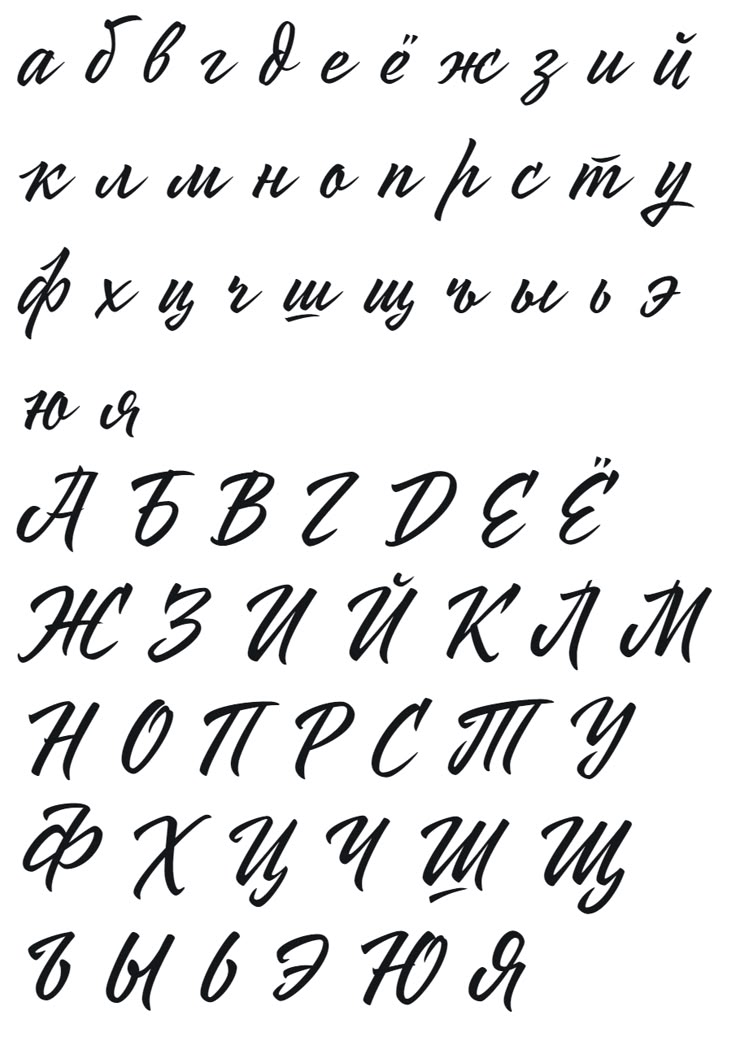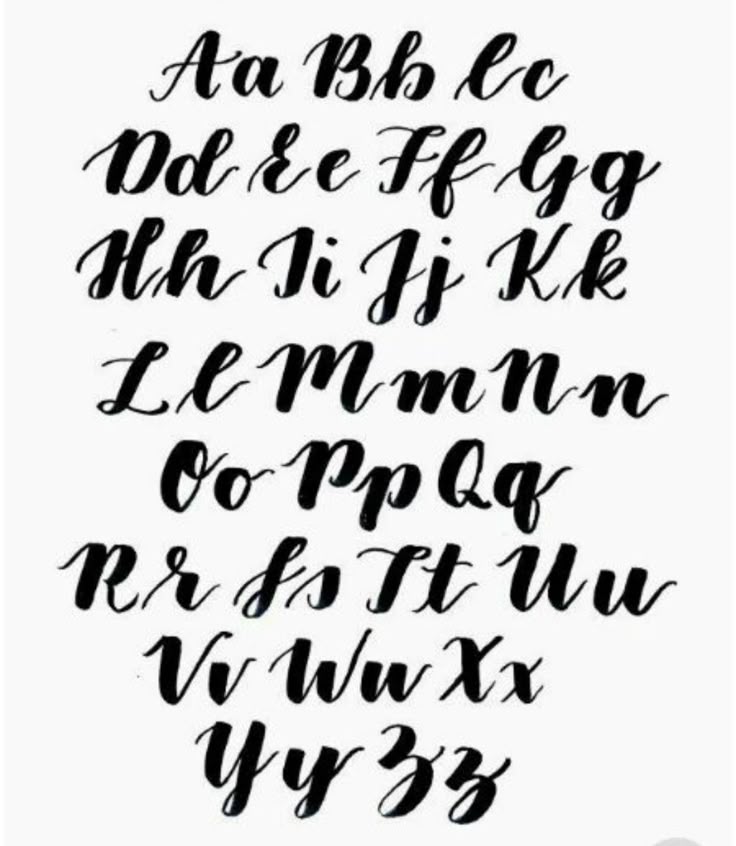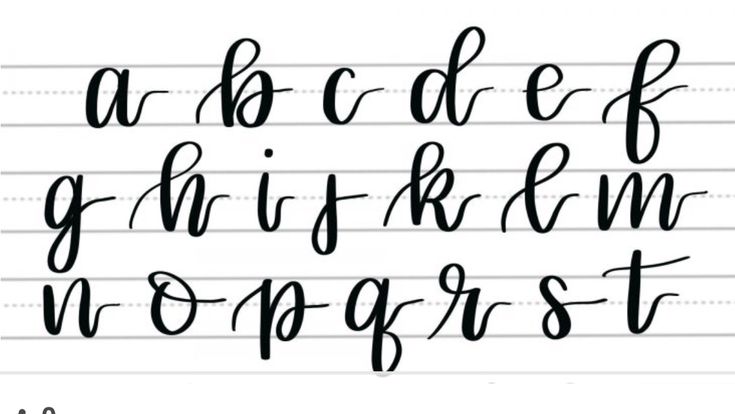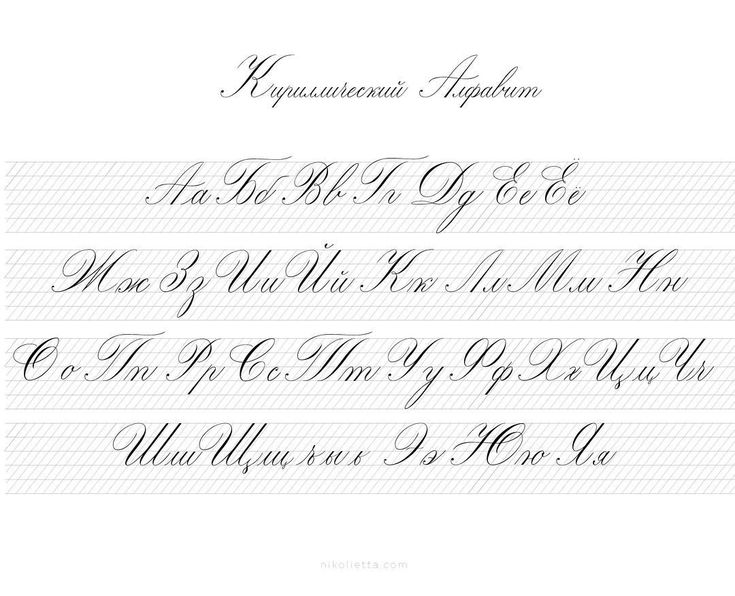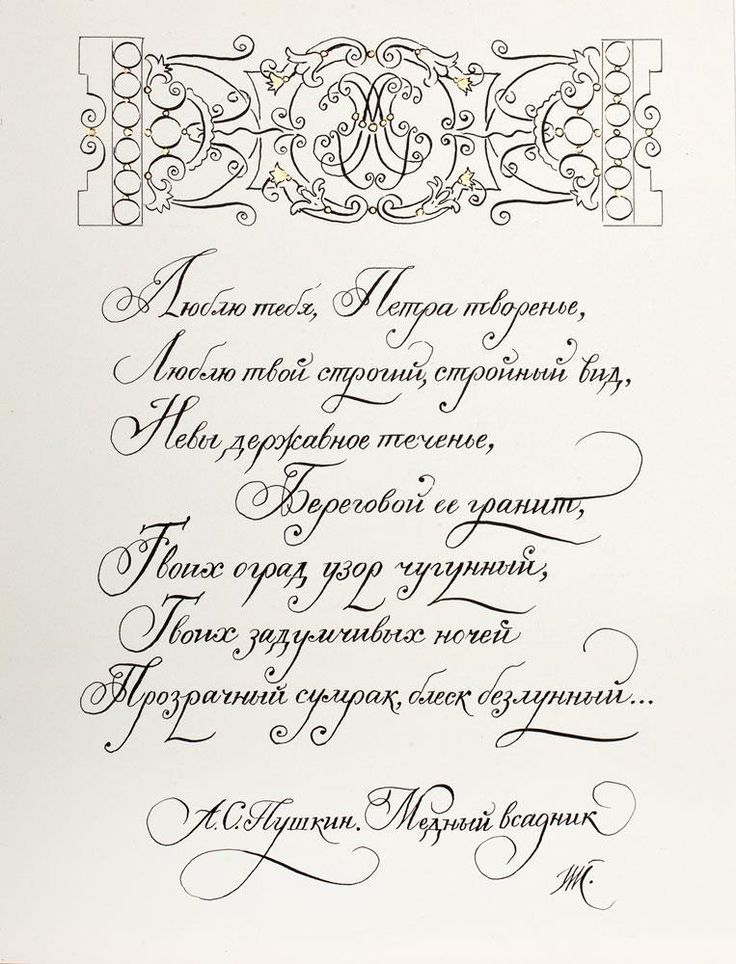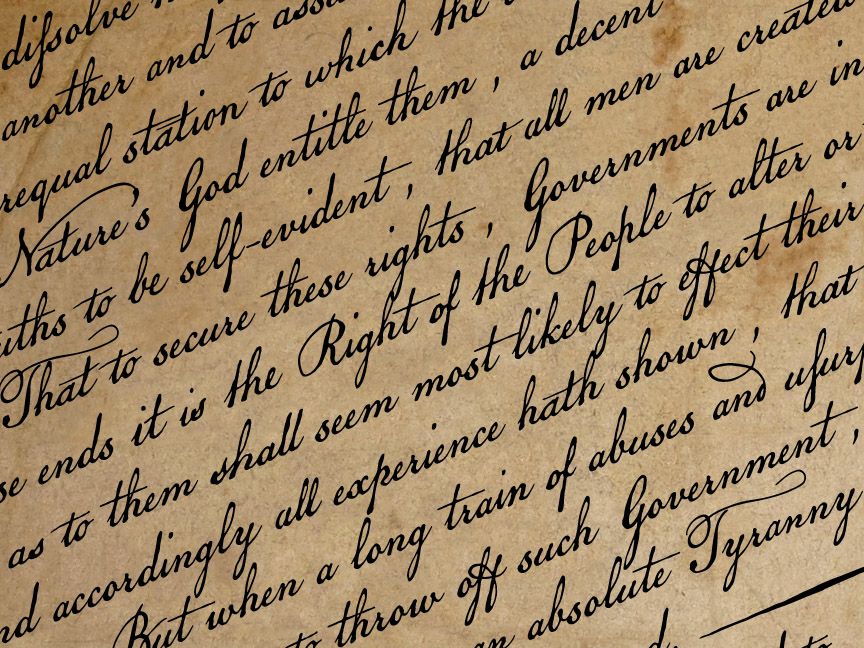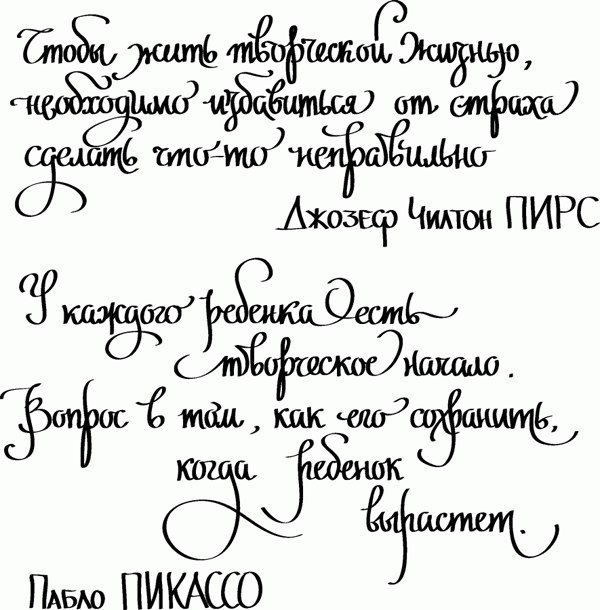
Рукописные шрифты и графология
Замысел статьи возник случайно. В руках графолога, далёкого от компьютерной техники, оказалось письмо, набранное шрифтом Коррида. «Какой противоречивый характер, — воскликнул он. — Что за человек это писал? Кто он?»
Автор объяснил, что этого человека на самом деле не существует. И тут же возникла идея — рассмотреть вопрос подробнее. Вообще-то, графология не относится к сверхпопулярным дисциплинам, но требование представить, например, написанное от руки резюме при приёме на работу встречается не столь уж редко. Малоизвестность графологии и даже недоверие к ней — результат многолетней политики, при которой популяризация подобного рода инструментария считалась излишней.
Между тем, нас не удивляет, что темперамент и характер человека проявляются в десятках жизненных мелочей: в манере завязывать галстук или затачивать карандаши, в выборе породы собаки, в цвете любимого авто, даже в том, как расходуется столбик губной помады и стаптываются подошвы ботинок.
Тем более странно, если б наши личные качества не находили полного отражения в таком тонком и тесно связанном с деятельностью мозга процессе, как письмо от руки. Вот что говорится об этом в специальной литературе: «Данное положение является логическим следствием представлений о системном строении психики и мозга… Все психические процессы (действия) складываются как сложное целое, состоящее из взаимосвязанных между собой частей (или звеньев), и обеспечиваются набором действующих мозговых структур, объединённых в функциональные органы… Одно и то же звено может входить в различные психические процессы, соединяя их в этой общей точке пересечения. Соответственно, одна и та же структура мозга участвует в образовании нескольких психических функций… Письмо как специальное психическое действие является сложным, многогранным процессом, в котором принимает участие большое количество мозговых областей, каждая из которых вносит свой специфический вклад в этот процесс» [1].
С учётом сказанного связь между почерком и такими качествами, как вспыльчивость, болезненность или болтливость, уже не кажется фантастической.
Каллиграфия против графологии
Автору неизвестен ни один пример, когда рукописный шрифт строился бы на графологической основе. Практически все разрабатываются по наитию, с немалой долей случайности, следствием чего может стать неожиданный результат. Так, в каталоге шрифтов компании ParaType тридцать рукописных гарнитур, разных по качеству, характеру и происхождению. Любопытно рассмотреть их с точки зрения графолога.
Исключим сразу группу шрифтов, основанных на канонических почерках разных стран и времён. Таковы ITC Цапф Чансери, Инглиш 157, Прописи, Петровская скоропись,
Шрифт ITC Цапф Чансери (дизайнер Герман Цапф, кириллическая часть доработана Владимиром Ефимовым при участии Геннадия Барышникова) основан на курсивных почерках эпохи итальянского Возрождения, в особенности писцов Папской канцелярии в Риме. Инглиш 157 (версия фирмы Bitstream шрифта Английский рукописный фирмы Berthold, кириллическая версия Владимира Ефимова) — шрифт в стиле английской каллиграфии XIX века. Название Прописи (дизайнер Манвел Шмавонян) говорит само за себя. Шрифт Петровская скоропись (дизайнер Геннадий Фридман) создан на основе образцов русской рукописной скорописи начала XVIII в. Каллиграфические почерки — предмет искусства, и графология их не рассматривает. Не несут личной информации прописи, стандартизованный чертёжный почерк и т. п.
«Личностные» шрифты
На другом полюсе находятся четыре варианта шрифта Пушкин (дизайнер Геннадий Фридман) и любые заказные шрифты, призванные точно имитировать руку конкретного человека.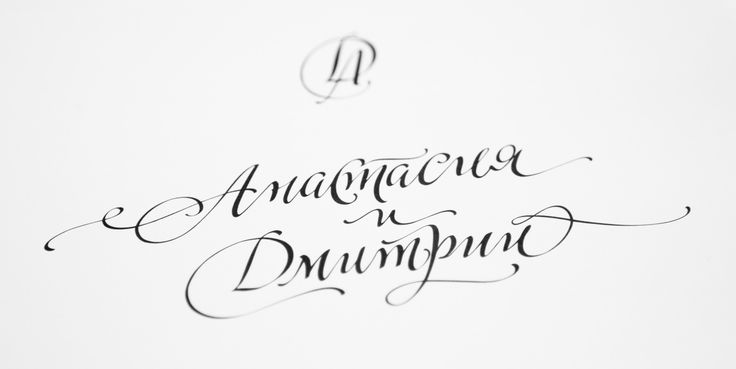
Наибольший интерес вызывают шрифты, в аннотациях к которым говорится, что «в основе лежит неформальный рукописный почерк». Их графологический анализ не столь бессмыслен, как могло бы показаться. Он даёт хотя и гипотетический, но вполне связный, логичный портрет, например, такой: «Эдвенчер — почерк энергичного, напористого, контактного человека, в котором любовь к комфорту борется с честолюбием; просматривается желание “соответствовать”, быть “на уровне”, принадлежать определённому кругу. Такой человек может предлагать необдуманные решения, настаивать на них, а в случае неудачи обвинять окружающий мир».
Разумеется, это не портрет дизайнера шрифта или человека, почерк которого послужил для шрифта прототипом, тем более что прототипов может быть несколько. Здесь могут, конечно, прослеживаться отдельные черты реальных характеров, но в сочетаниях, по которым «трудно было бы правду узнать».
Ведь истории многих шрифтов полны поворотов: шрифт может создаваться одним художником по эскизам другого, затем перерабатываться третьим, а четвёртый доделывает кириллическую часть. Получившаяся «шрифтовая личность» начинает жить собственной жизнью. Пусть читатель не может ничем объяснить своего впечатления — подсознательное влияние шрифт, безусловно, оказывает. Нетрудно предположить, например, что псевдорукописный текст, похожий на почерк доброго, умного, весёлого и лёгкого в общении собеседника, скорее всего, расположит к себе читателя, а «почерк» угрюмого неприятного субъекта будет подсознательно блокировать желание общаться. Кто знает, может быть, в этом таится ещё один, до сих пор не разработанный метод рекламного воздействия?
«Бетина Скрипт. Неутешительная картина почерка человека неуравновешенного, способного на неожиданные выходки, импульсивного и претендующего на бытовое лидерство. Но пишущий таким образом человек способен учитывать собственный житейский опыт и может быть неплохим тактиком, если кто-то предложит ему подходящий мотив.
Почерк неплох для рекламы сигарет и пива».
Стоит сказать, что компьютерные «почерки» в том виде, в каком они обычно используются сейчас, лишены важнейших характеристик живого почерка — вариативности знаков, переменного наклона строк относительно листа бумаги, индивидуальных особенностей при переносах слов и формировании края текста. Если бы живой человек писал тексты от руки подобным образом, это свидетельствовало бы о больших проблемах. Но поскольку читатель привык видеть напечатанный текст именно таким — выровненным, идеально регулярным, это обычно не оказывает негативного эффекта на восприятие.